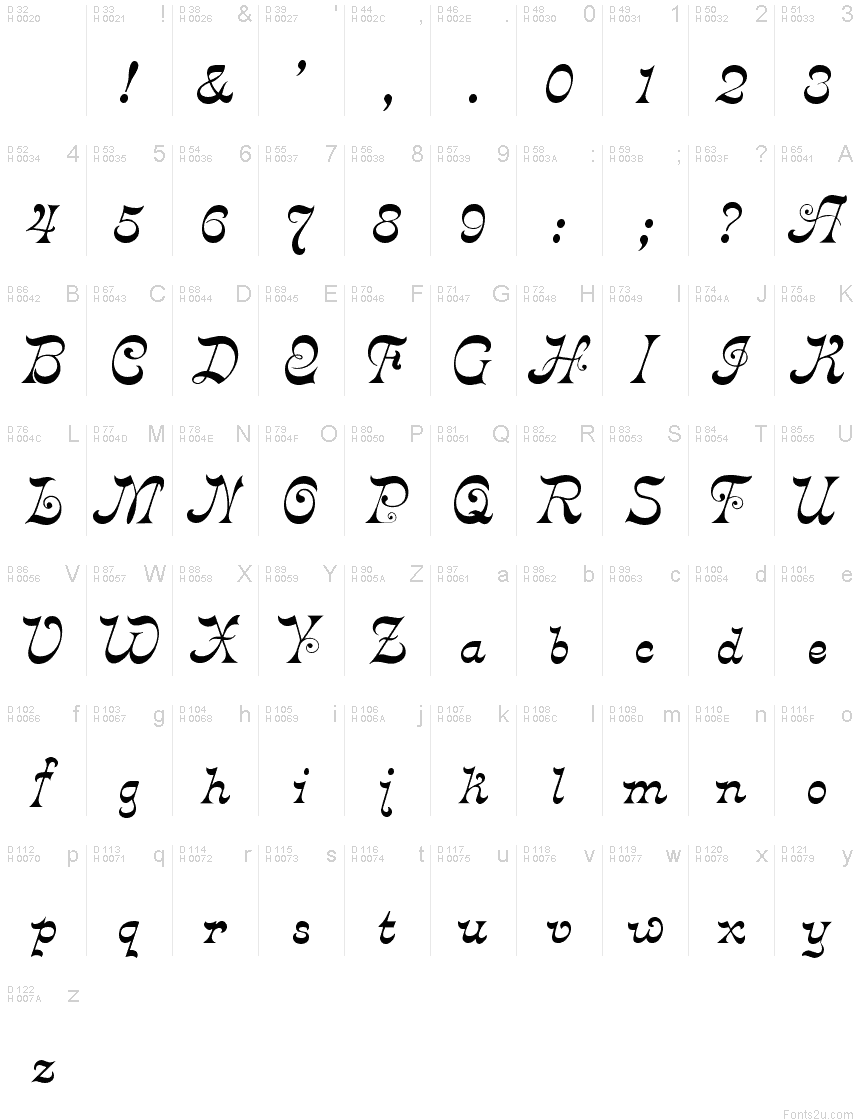
Derniere è un font script dal tratto fluido, caratterizzato da linee eleganti e sinuose e da una delicata inclinazione verso destra. Le lettere sembrano scritte a mano con un pennino, conferendo a ogni parola un ritmo morbido e cerimoniale, pur mantenendo una chiara leggibilità. Grazie alle sue curve calligrafiche, è la scelta naturale quando si desidera una tipografia dal carattere personale ma ricercato.
Questo font gratuito è perfetto per inviti di nozze, locandine di eventi, loghi di boutique, packaging, biglietti d'auguri e grafiche con citazioni. Derniere dà il meglio di sé nei titoli di grandi dimensioni, dove le sue curve possono respirare; l'ideale è abbinarla a un font sans serif semplice per i testi di accompagnamento. Usalo per donare un tocco delicato e romantico al tuo branding o ai tuoi titoli, senza mai compromettere la leggibilità.